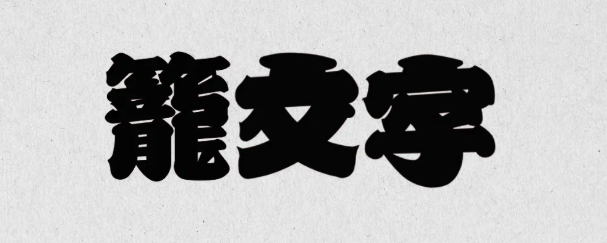
笼字(篭文字;かごもじ)是由浮世绘艺术家歌川国芳的弟子歌川义金和梅增亭源优创立的广告字体。 它起源于浅社钞票,此后被广泛应用。
笼字并不是文字形态的名称,而是在大的揭匾、招牌等大的文字,以及堤灯、行李箱等凹凸不平的表面上书写的文字,指用“笼抄”(在不平的材质上书写文字,难以一笔书写的情况下,先写出文字的轮廓,然后涂在其中的手法)书写的文字。
笼文字的笔划很粗,外围微呈四角形。这是在江户时代,写字工匠为了让字体个性化,而将夸张地装饰赋予文字所导致的。笼文字的起笔收笔急促且果断,虽然笔画间隙狭小,但是整个的布白匀称,丝毫不影响文字的阅读识别。